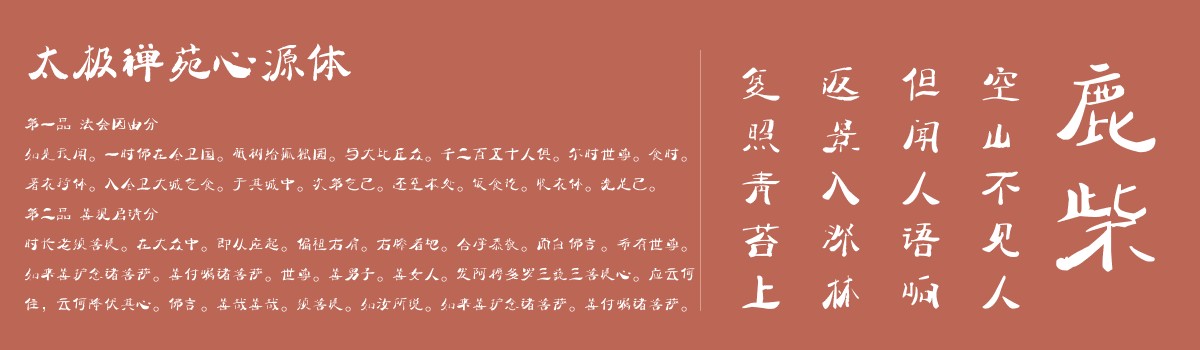
字体名称:太极禅苑心源体
太极禅苑心源体是由阿里巴巴太极禅苑员工童晓君(花名:紫摩)书写的一款字体原型,晓君自幼喜爱国学和佛学,2015年曾在泰国短暂出家,自三年前练习书法至今,书法的练习方式以抄写经书为主,她抄写的经书曾被多位企业家收藏,其书法风格隽秀清丽,欣赏其书法作品时似乎能感受到心底的平静,在静谧中寻找一种通向人生心灵深处的那盏明灯,字里行间透露出一种禅文化的阴阳平和,太极禅苑拥有独立版权的字体,由叶根友字体团队制作。